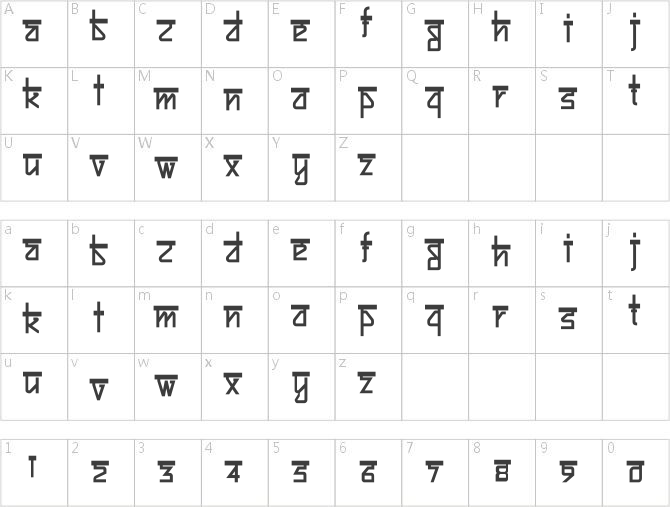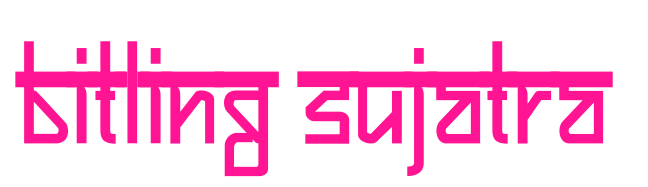
Bitling sujatra 詳情頁
字體名稱: Bitling
Bitling sujatra
Bitling sujatra字體字庫是一款讓人賞心悅目、百看不厭的英文字體,適合各類廣告和產(chǎn)品包裝設(shè)計應(yīng)用,字體大小0.01MB,格式為ttf字體,上傳用戶是舒甜咖啡,作者/版權(quán)方為未知